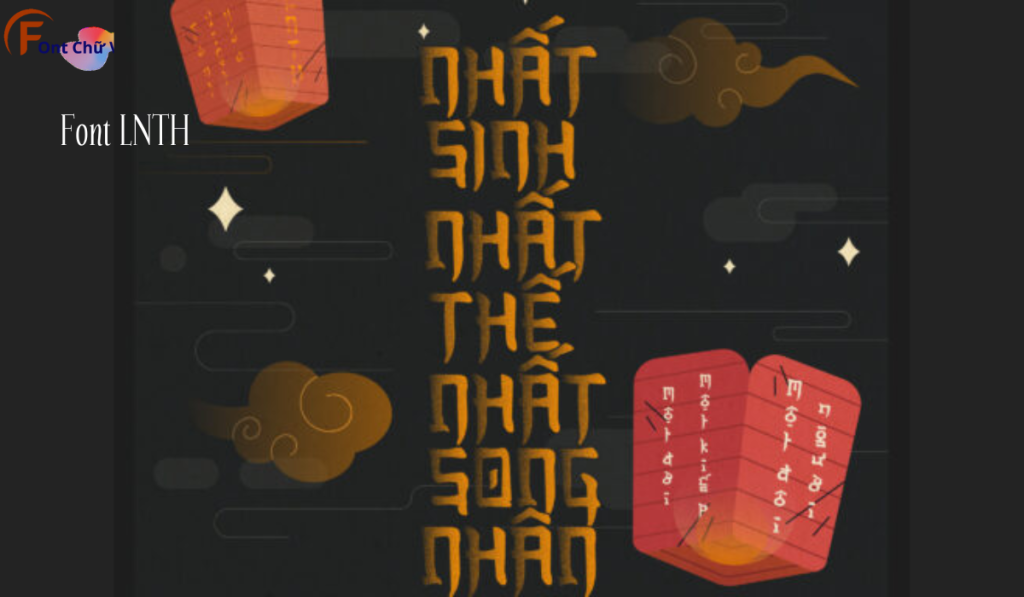
Font LNTH aAnnyeongHaseyo Việt Hóa
Tác giả: LNTH
Ngôn ngữ: Tiếng Việt, Tiếng Hàn
Phân loại: cá tính
Kiểu chữ: không chân
Độ dày: thường
Font LNTH aAnnyeongHaseyo Việt Hóa là một font chữ hiện đại, thuộc bộ LNTH, với thiết kế đơn giản và tinh tế. Phong cách của font này phù hợp với các dự án thiết kế cần sự hiện đại và thanh lịch, như logo, tiêu đề, hoặc bảng hiệu. Font LNTH aAnnyeongHaseyo Việt Hóa mang đến sự hiện đại và dễ nhận diện, ứng dụng trong các lĩnh vực sáng tạo. Đặc điểm hình dạng của font bao gồm các đường nét gọn gàng và tinh tế, giúp tăng tính thẩm mỹ và sự chú ý. Việc Việt hóa font giúp người dùng dễ dàng sử dụng trong các thiết kế tiếng Việt, mang lại sự tiện lợi và linh hoạt.